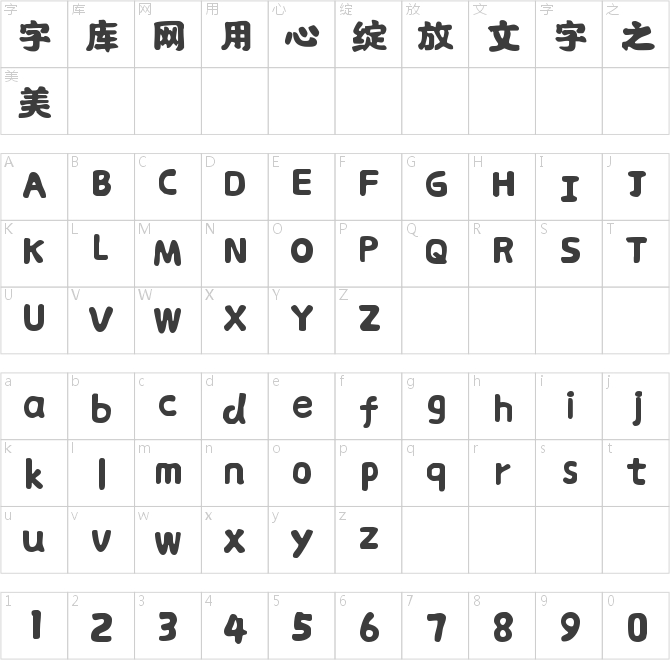
字魂226號-國潮手書(混沌版) 詳情頁
字魂226號-國潮手書(混沌版)字體下載zihun226hao-guochaoshoushu(hundunban)
字魂226號-國潮手書(混沌版)是一款手寫字。字體字型偏方,筆畫中減少了過多的處理和筆勢,字形厚重、飽滿,每個字都獨具風情,適合現代廣告、電視等商業設計應用。